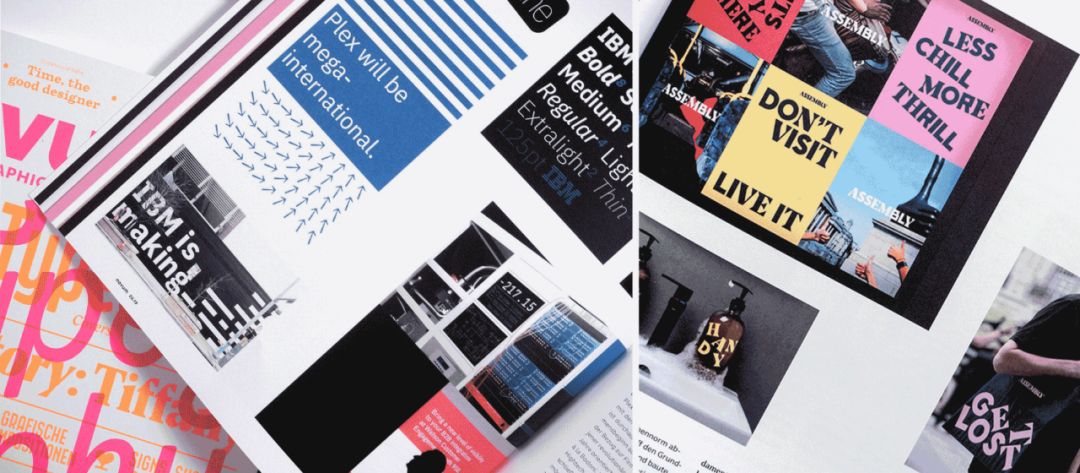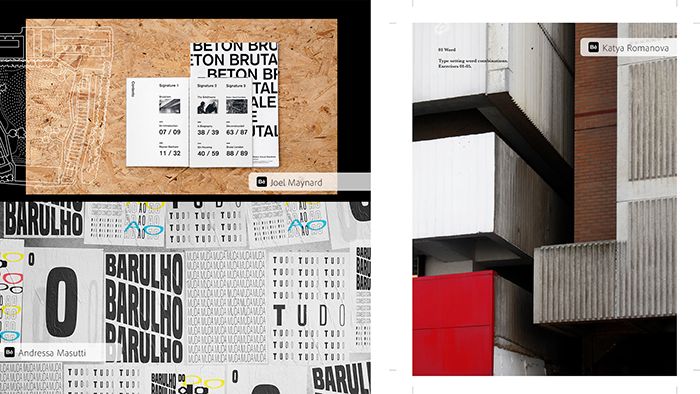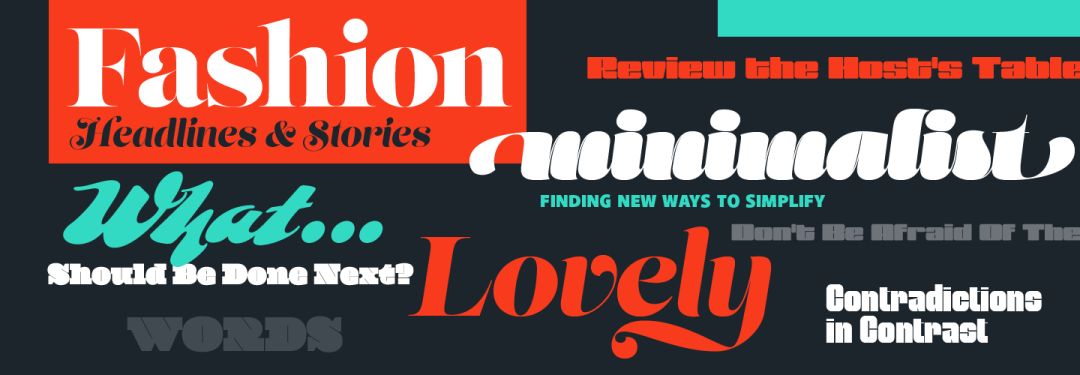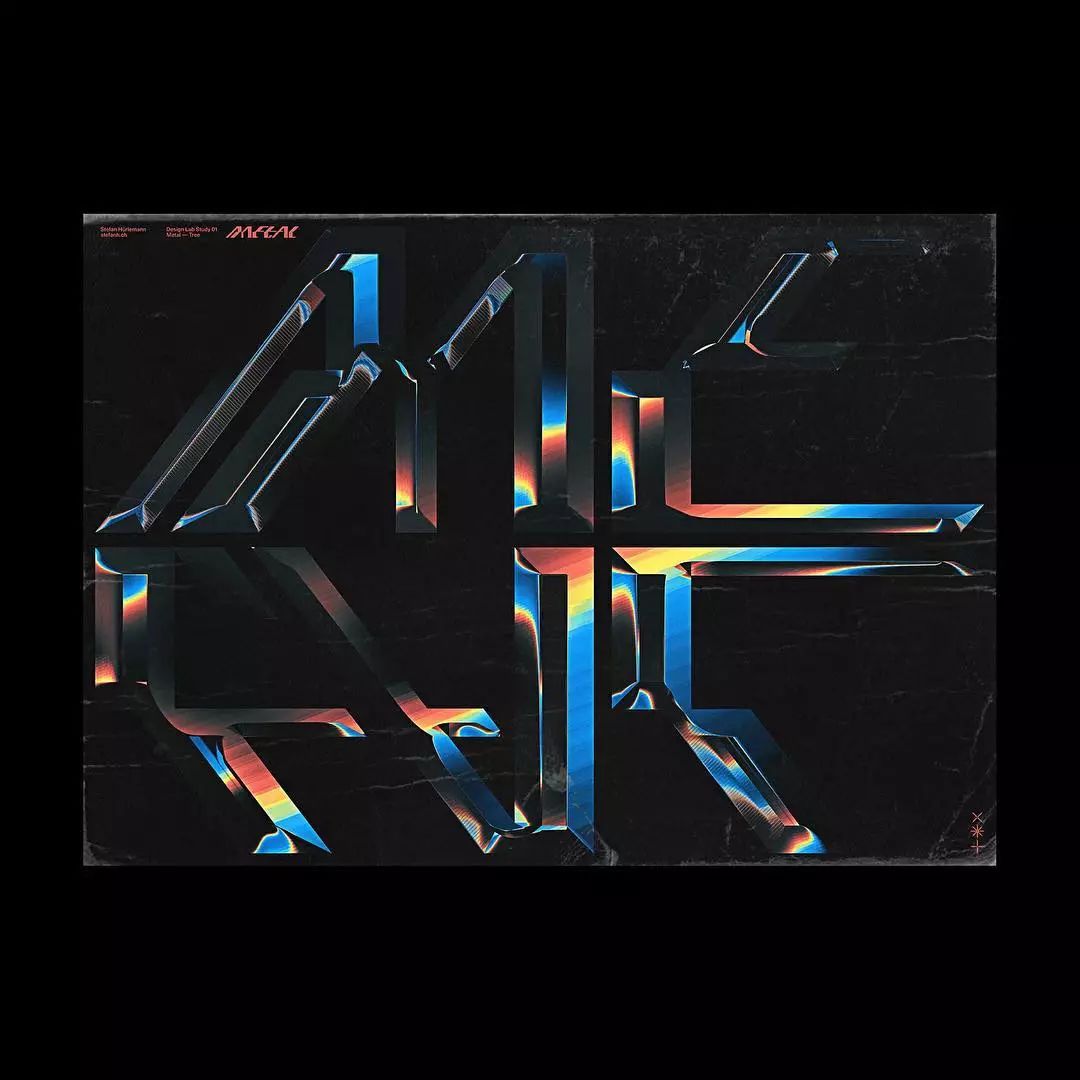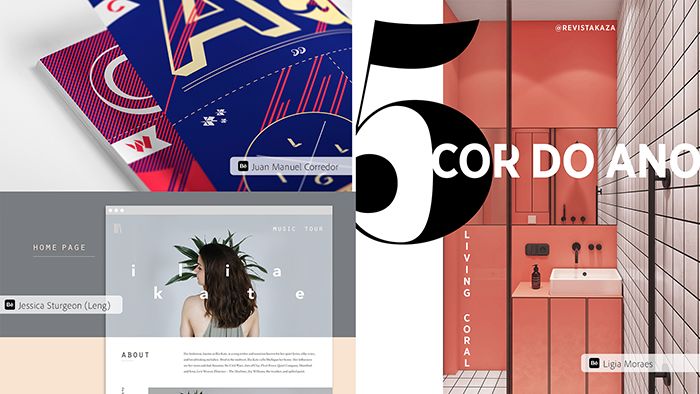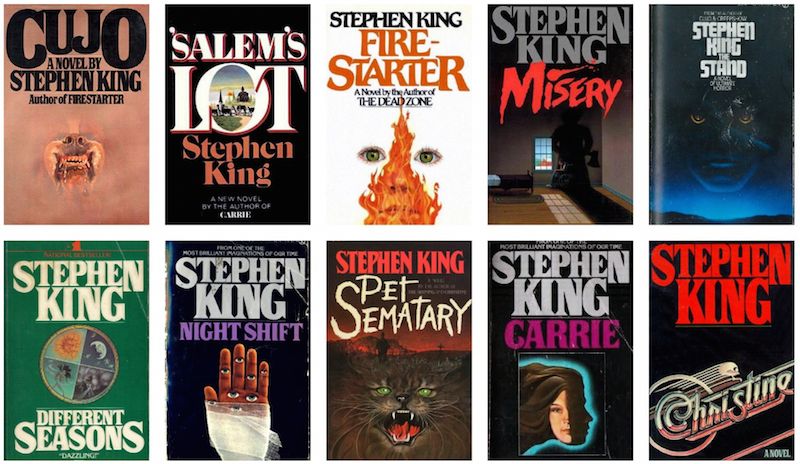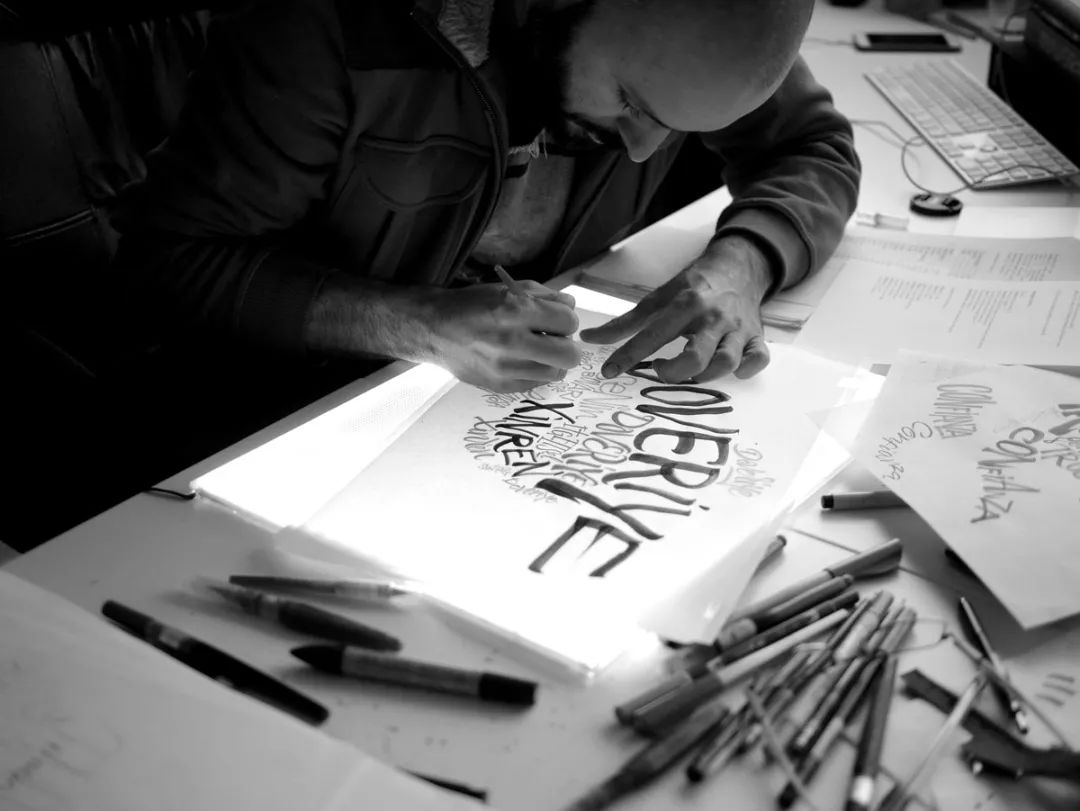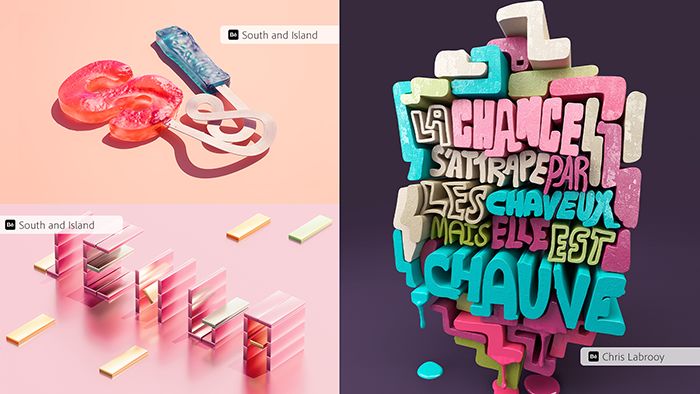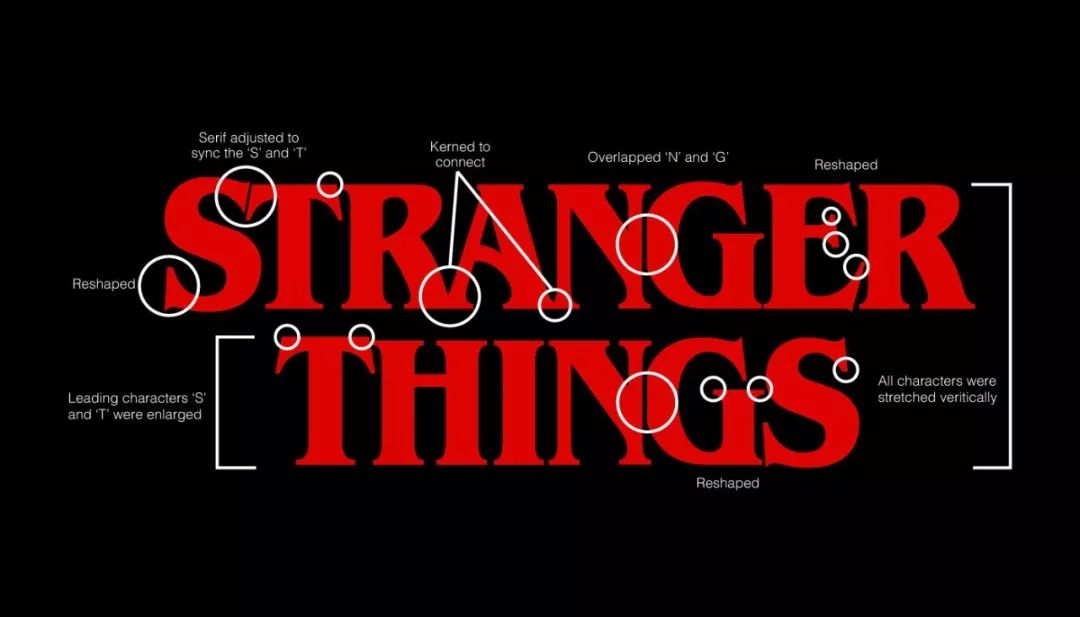
2019字体设计的八大趋势,你都了解吗?
“让人们学会如何‘看’字体这件事,
正变得史无前例的重要。”
“The need to help people
understand how to see typography
is more important than ever.”
身为设计师,现在的我们越来越依赖使用“字体”来进行设计中的条理叙述。有了日益先进的操作工具及层出不穷的新兴字体,字体设计也变得前所未有的自由。
现在,就让我们一睹2019年字体设计的八大趋势吧!
/ 精简版 /
最简单的无衬线体
高对比度
野兽派
可变字体+动态展示
粗体+框线
手写字体
怀旧字体
3D+AR字体
01
﹏
最简单的无衬线体
Minimal Sans Serifs
“黑体字永不过时。”
“Sans serifs will never die.”
无衬线字体在平面设计中有着非常良好的表现。它们略显复杂的现代神秘感给设计师创造了表达和传递情绪的空间。
同时,无衬线成为“干净、整洁”设计的新标准。
“现代无衬线字体已经变成诸如Helvetica(一种被广泛使用的的西文字体,于1957年由瑞士字体设计师爱德华德·霍夫曼(Eduard Hoffmann)和马克斯·米耶丁格(Max Miedinger)设计。它是苹果电脑的默认字体,微软常用的Arial字体也来自于它)这样的主流代言人。”
高对比度
High Contrast
“更极致的定制性及可操作性。”
“More extreme customization and manipulation.”
随性的设计实验在设计界已经不算什么了。事实上,实验性作品越来越受到推崇。那怎么才能紧跟平面设计的巨大潮流呢?
高对比就是你的工具。
现在许多字体工具都允许设计师随意改变字体的粗细、重叠、间隔……太多的地方可供我们进行改变和调整。
填补一些空白。或许在下一个UX或品牌形象设计中,你可以试试利用高对比来完成。
野兽派
Brutalism
“明知山有虎,偏向虎山行?”
“What can I do with this that I’m not supposed to?”
野兽派喜欢把字体直接推向页面的边缘——许多设计师正纵身跃入其中,尝试些他们本不该做的事。
“这是一种全新的后现代主义。这对规则和标准产生了实实在在的冲击。”
字体公司Panagram Foundry在相关分享中说道:“这样的野兽派是在设计中创造张力的绝佳方式。”当一个未经加工和雕琢的设计直接跳在你眼前的时候,它立刻就抓住了人们的眼球。
设计:Stefan Huerlemann
野兽派的字体还能营造一种狂躁、反叛的氛围,这也是为什么在海报和实验项目中常见这种粗野的风格。
可变字体+动态展示
Variable Fonts + Kinetic Type
“这很可能是至今字体设计最伟大的发现之一。”
“Possibly, one of the greatest type discoveries, yet.”
随着开放字体的改革创新,从前难以想象的字体及图形的处理方式进入了一个可以无休止放大缩小的定制开放新纪元。
有了可变字体,你可以在给定范围内,对字体任意地放大、缩小,拉伸或者弯曲……可以让它调整成你想要的比例、适合作品的匀称效果,甚至是连续的动画。
现在,这项技术开始让设计朝着越来越有趣的方向发展。
“如果你想跳出静态设计,不妨试试可变字体吧。它可以让你有更多的创作自由,让字体与设计有更多的互动。做与他人一样的设计?你大可不必。”
粗体+框线
BOLD + Outlined
“比文字本身还有力的绝美艺术。”
“Show-stopping art that’s louder than words.”
越粗越好。
字体中,没有最强劲,只有更强劲。全员大写、大小写相交错等等都能让人们驻足。
有轮廓边框的字体让字体能更有趣地过渡到平面设计中。尤其是在时尚、报纸杂志等中,这样的轮廓字体非常常见,可以说它们在开放性的构图里表现完美。
此外,彩色的字体也从未从设计中分离。再把今年的视觉趋势调色盘用上,你就是全场的焦点。
不妨把它用在你下一个杂志、文章或某个品牌项目中。
手写字体
Hand-Lettered Fonts
“‘个性’正得到前所未有的重视。”
“Individuality is more important than ever.”
是的,众所周知,手写字多得到处都是。但是,手写字已经用滥了吗?
并没有。尤其这关联到“个性”的时候。
“手写字几乎是一种字体的美妙初体验。在西方文化,特别是阴性美学中,模仿手写的字体已经存在了很久。”
图中Hiii Typography 2013英文组金奖获得者-Joluvian正根据书法手写字为灵感创作
最近几年,手写字体具有越发强有力的承载性,且大有越来越强调风格化的趋势。它们不再只是局限在绵软或极具学院风,而变得可以更加大胆、前卫。
一千个手写,一千种不同。手写字体间的细微差别也带给设计更多的独特性及不可复制性。
怀旧字体
Nostalgic Fonts
“人类的本质就是复读机。”
“When generations keep repeating itself.”
每个人都魔怔似的想要设计出那个最能追忆80年代的字体。
距离Repro Script及Bodoni(由Giambattista Bodoni 于十八世纪晚期首次设计出的衬线字体)的创造使用已经过去太久。但是数十年来,人们还前仆后继地希望能创造出一个既现代又引人陷入沉思与回忆的字体。
在这其中,我们可以发现阅读字体是如何与读者的情绪建立联系。
例如,设计师Ed Benguiat创造乐《奇怪物语(Stranger Things)》字体——一种让人看了不禁想起诸多经典恐怖作品及80年代流行文化的字体。
是的,兜兜转转,怀旧、复古也总是在设计中反复出现。
该字体启发自斯蒂芬·金的小说封面
这些怀旧风的字体常常运用在电影海报、音乐宣传单、活动宣传等项目中。这里还有一些极具90年代风的字体设计。↓↓↓
90年代风字体案例
3D+AR字体
3D + Type for AR
“新一级的设计,新一级的字体。”
“Next level type, for next level design.”
时代的车轮不断前进。设计师们也紧随其后,开始实验在新的维度空间创作作品。那字体呢?
随着VR、AR、照片虚拟现实化、3D等新兴技术的产生,新一维度的设计也应运而出。设计变得可以更加自由地与场景交互。
有了3D技术,你可以让字体得到拉伸、弯曲、旋转等等来改变字体的呈现方式,以创造一种浸入式体验。
像是Andrew Johnson这样的设计师们正在不断探索字体设计的边界,看看3D技术究竟可以让字体变成什么样。
Andrew Johnson设计的这种字体呈现可以根据观看角度自动做相应调整。